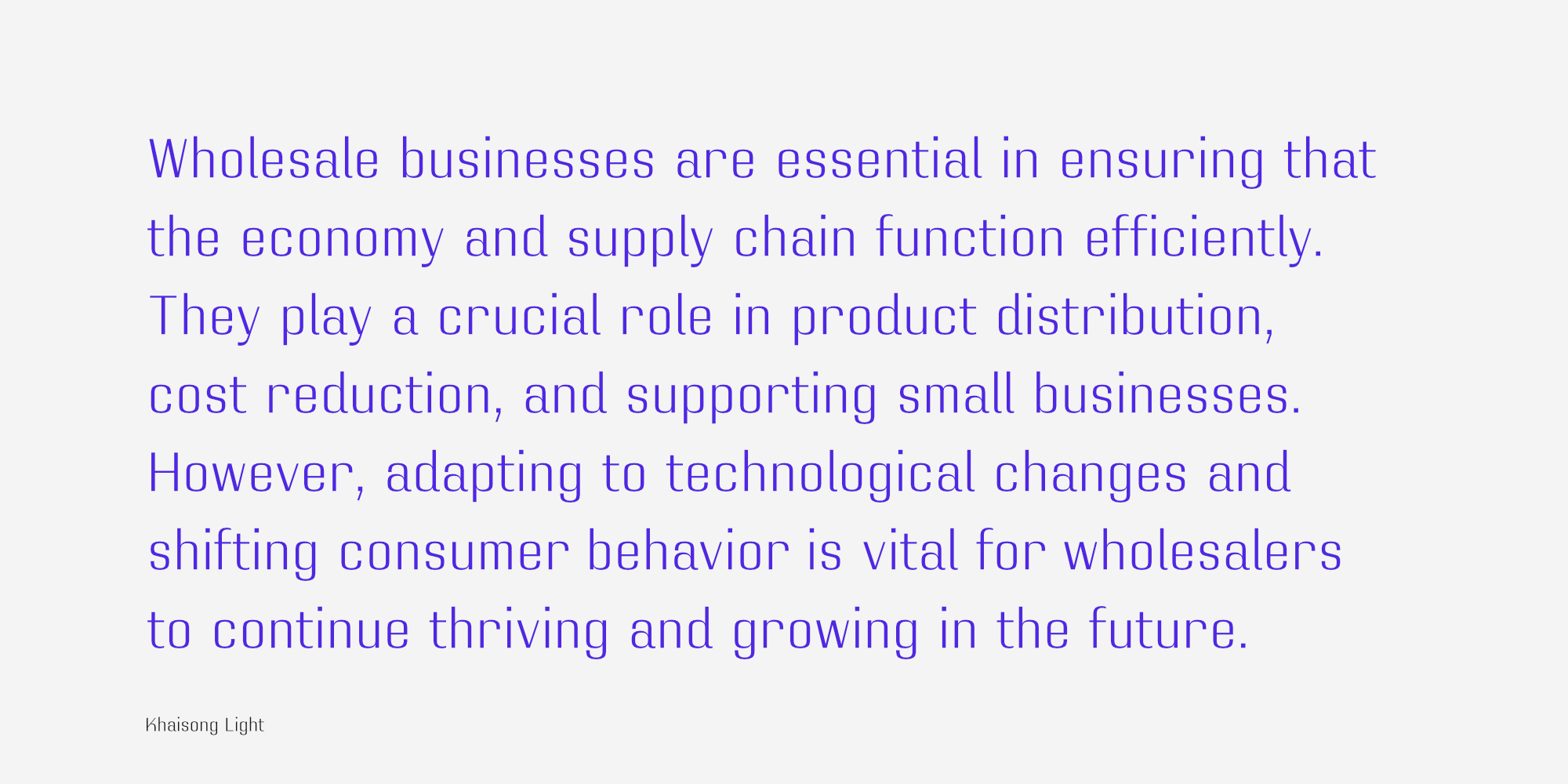
ขายส่ง | Khaisong
ชื่อฟอนต์ : ขายส่ง | Khaisong
ขายส่ง เป็นแบบอักษรคอนทราสต์แซนเซอริฟ ตัวอักษรมีลักษณะ Geometric ให้ความรู้สึกเป็นทางการแต่ไม่แข็งกระด้าง มีความเรียบง่าย เหมาะสำหรับสื่อประชาสัมพันธ์ที่ต้องการสื่อสารเนื้อหาเชิงธุรกิจและองค์กร โดยยังคงความอ่านง่ายและความเป็นมืออาชีพ แบบอักษรนี้ประกอบด้วย 18 รูปแบบ ครอบคลุมน้ำหนักเส้นตั้งแต่บางที่สุดจนถึงหนาที่สุด โดยรองรับทั้งชุดอักษรลาติน 1 และอักษรไทย
Creator : อานุภาพ ใจชำนาญ (Anupap Jaichumnan)